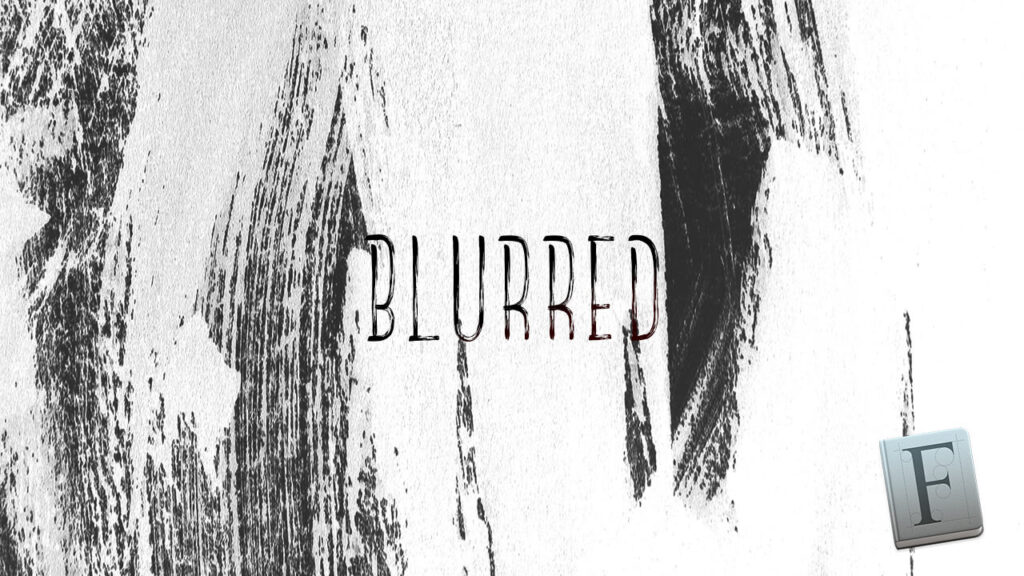
【全て無料】掠れ具合がいい感じの『掠れフォント素材』をまとめて紹介!!
今回は掠れ具合がいい感じの『掠れフォント素材』を紹介していきます。
ぜひお気に入りのフォントを見つけてデザインに生かしましょう!!
Bengal Claw
源界明朝
DEATHNOTE
Lee Claw
アストロゼット
Takota
Againts
Jumper Handwritten Font
Oh Script!
略字超少明朝ステンシル風
Road Rage
躍動感のできるエッジの効いたかっこいい無料フォント素材で、私もお気に入りです(´∀`*)
Punisher